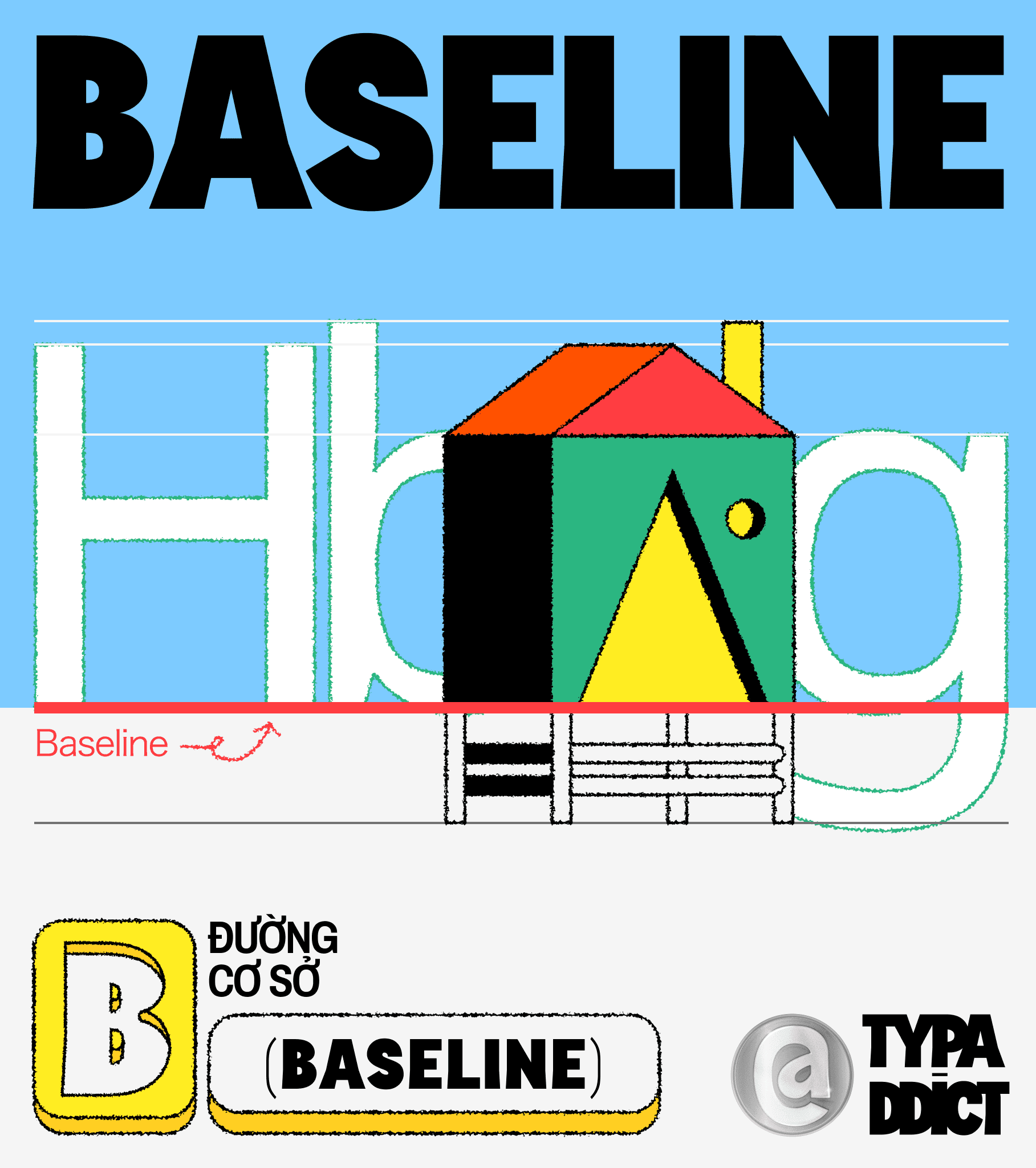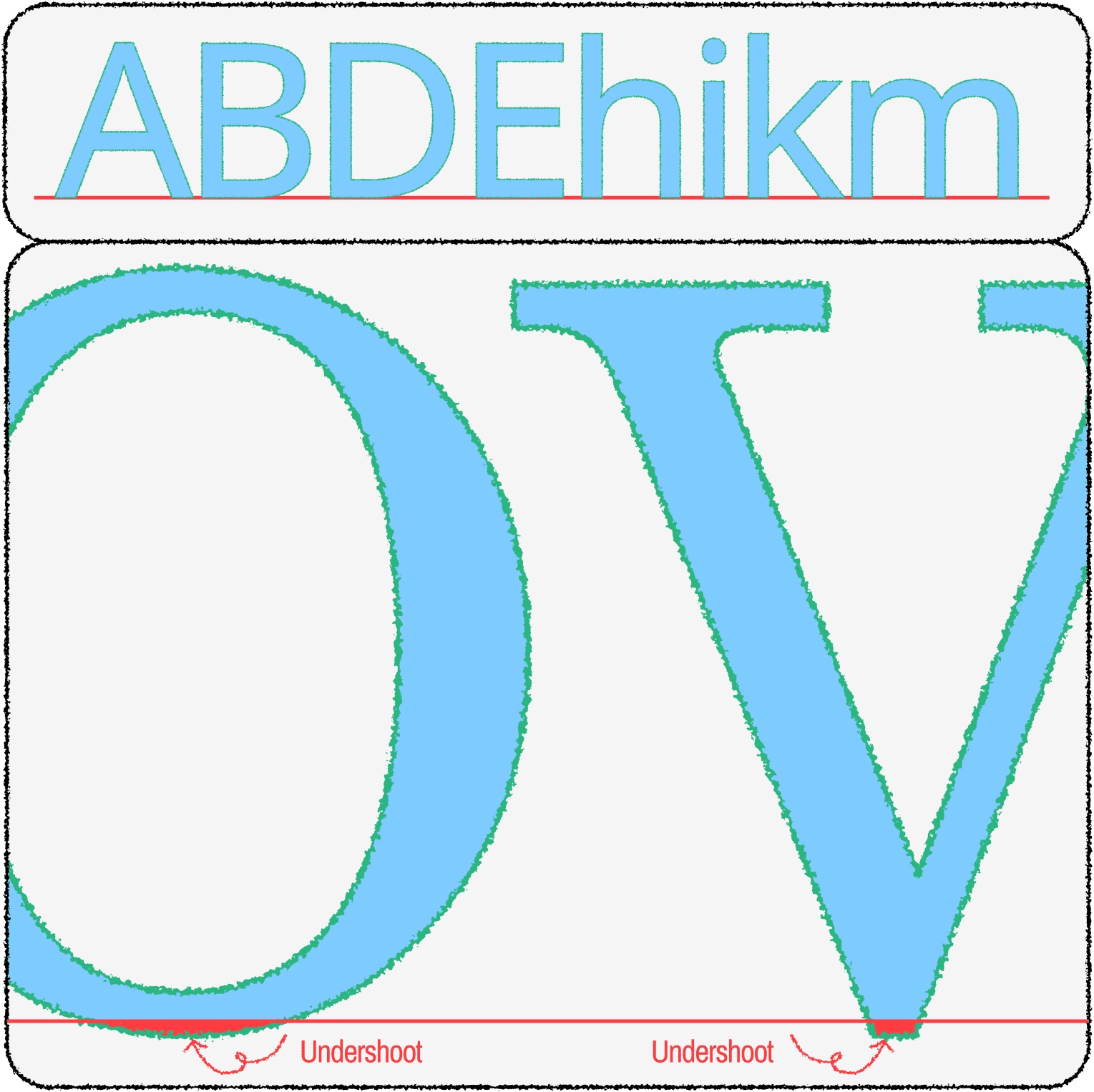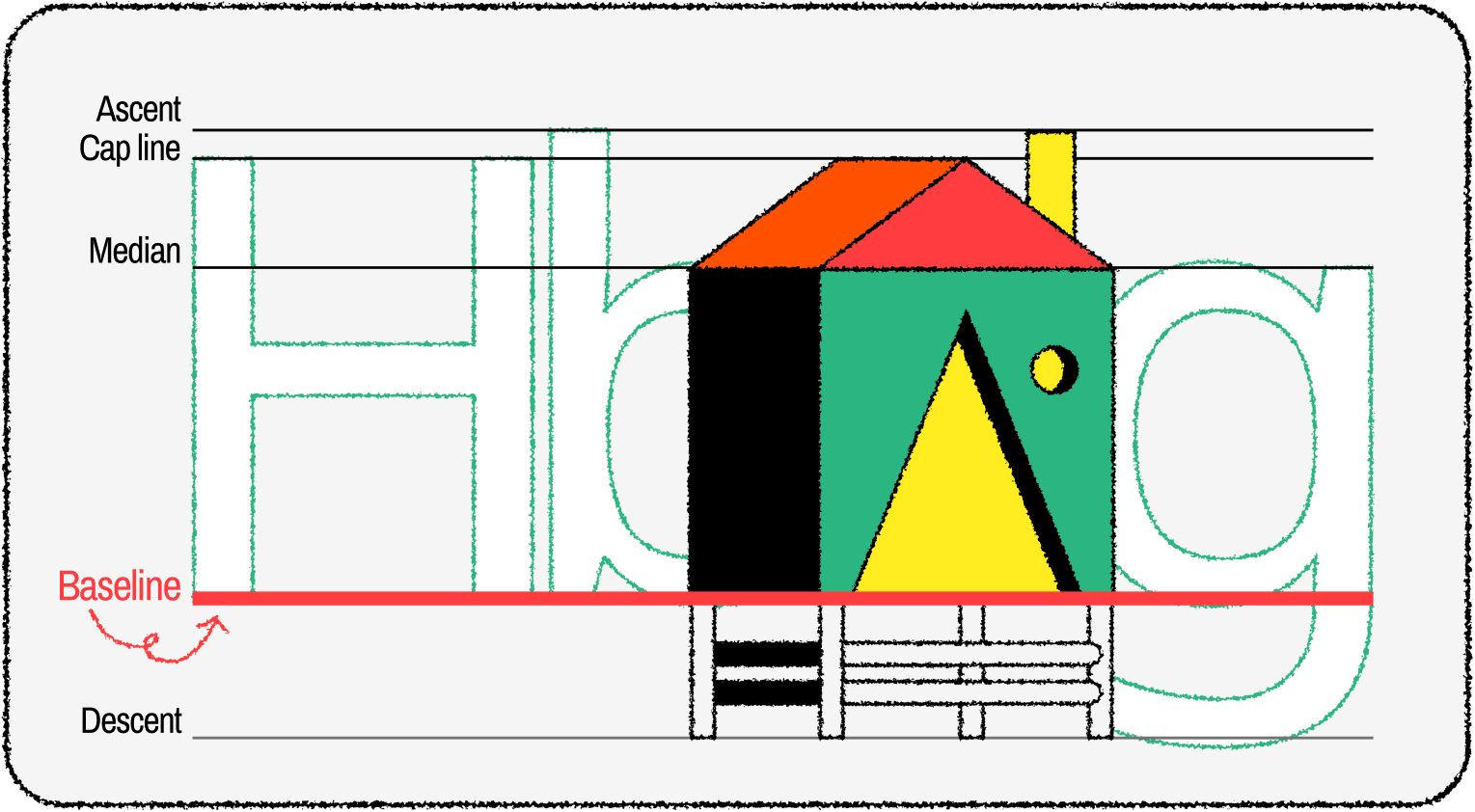
Nếu xem việc thiết kế một ký tự như việc xây dựng một căn nhà, BASELINE (đường cơ sở) chính là phần đất nền nơi từng chiếc cọc móng được đóng xuống, nơi từng viên gạch được xây dựng lên.
Baseline được xem là đường tham chiếu cơ bản nhất, cùng với các đường “median”, “cap-line”, “ascent”, “descent" góp phần kiểm soát vị trí và tỉ lệ của các ký tự trong bộ thiết kế chữ.
Baseline nằm ở vị trí điểm thấp nhất của hầu hết các chữ cái, đặc biệt là các chữ cái có phần dưới chữ ở dạng bằng.